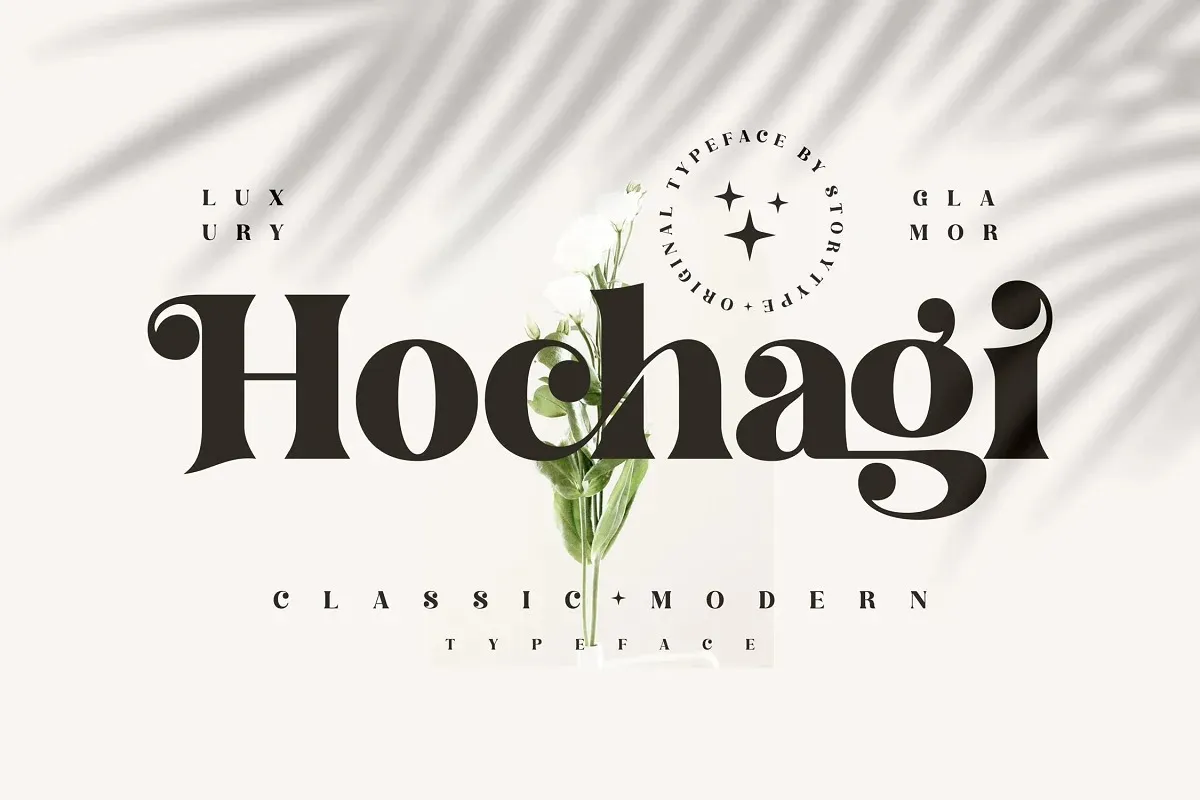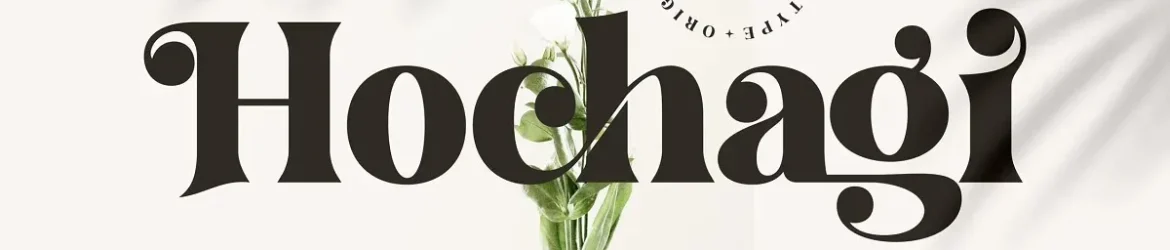
Esta é uma fonte serif moderna e robusta criada pelo Storytype Studio. Com letras grossas e elegantes, ela se destaca para uso em logos sofisticados e luxuosos, títulos de livros ou filmes, marcas fashionistas, revistas, roupas, artefatos de escrita, citações e muito mais. A Hochagi Font é perfeita para dar um toque sofisticado a qualquer projeto visual, seja em logotipos, embalagens ou até mesmo textos digitais. Combinada com a sua elegância clássica, ela traz uma sensação de história e qualidade que torna este tipo de fonte perfeitamente adaptável a diversos usos. Atrair novos clientes pode ser um processo fácil quando você usa a Hochagi Font para seus projetos gráficos.